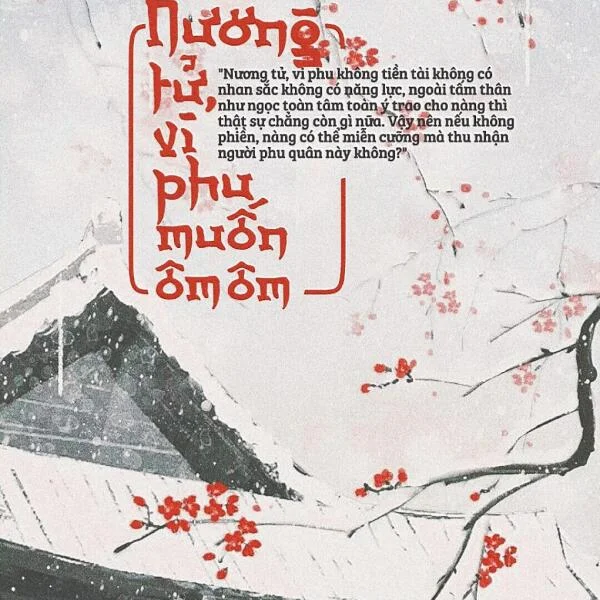
Tổng quan về 8 font
Đây là 8 font chữ Việt Hóa khá chất lượng được mình sưu tầm, những font chữ này khá phù hợp cho các bạn sử dụng để thiết kế chủ đề về trung thu, cổ trang, các dịp lễ Tết... hoặc bất kỳ thiết kế nào khác mà bạn cảm thấy phù hợp.
Font Việt hóa cổ trang
Mẫu 1
Font Việt hóa phù hợp thiết kế trung thu
Mẫu 2
Font việt hóa thư pháp siêu đẹp
Mẫu 3